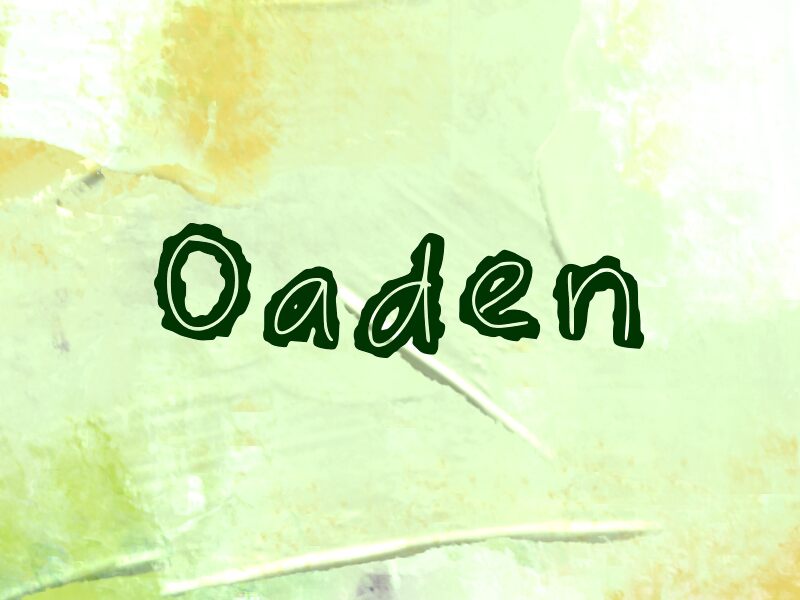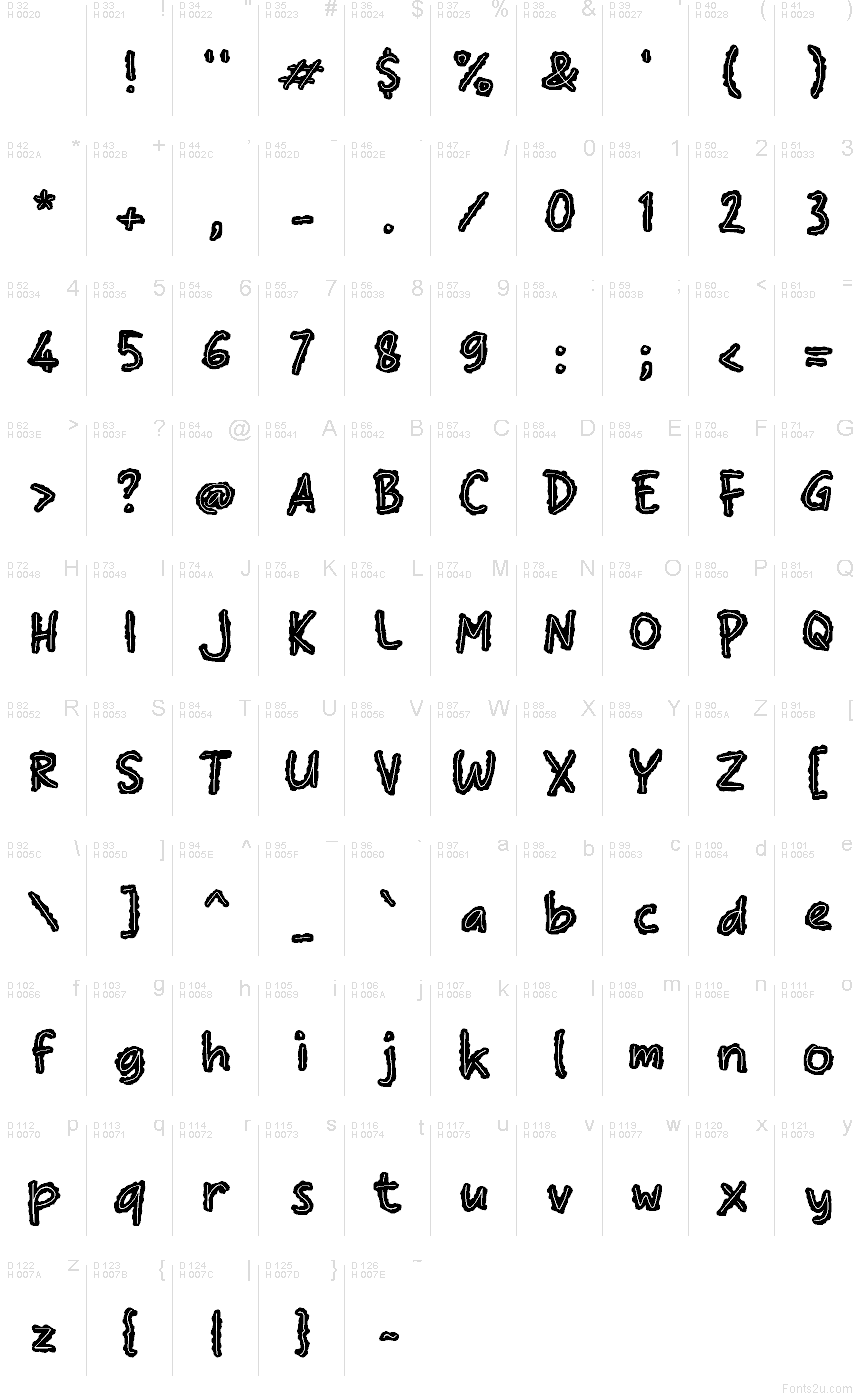
Oaden od Wep to darmowy font typu brush z lekko niechlujnym, nasyconym tuszem konturem, który wygląda jak ręcznie malowany, z nutką kreskówkowego stylu. Litery są pękate i nierówne, z poszarpanymi krawędziami i luźnymi pociągnięciami wewnątrz, co nadaje im żywy, autentyczny charakter, daleki od sztucznej perfekcji.
Dzięki temu Oaden świetnie sprawdza się na plakatach, okładkach zina, grafikach muzycznych, opakowaniach czy w zabawnych projektach brandingowych, gdzie darmowy font potrzebuje więcej wyrazistości niż grzeczne fonty typu script. Dobrze wypada też w krótkich tytułach, hasłach czy szybkich projektach logotypów, ponieważ masywna sylwetka i drgający rytm pędzla nadają charakteru nawet pojedynczym słowom.
Oaden
Prezentacja i próbka wizualna czcionki Oaden
Mapa znaków czcionki Oaden